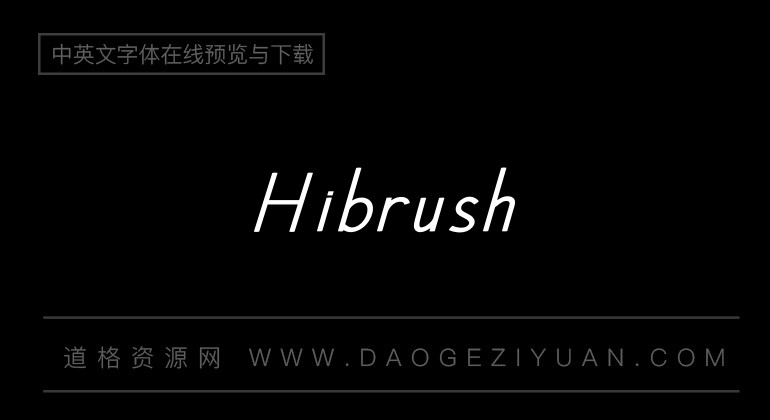
Hibrush 是一款由著名设计师 David Berlow 所设计的字体,它是一款非常优秀的斜体字体,具有非常强烈的视觉冲击力和非常独特的设计风格,它的字体结构设计紧凑而精细,可以让文字具有良好的表现力和清晰度。Hibrush 字体也可以用于多种不同的文字排版,比如标题、正文、图片文字等,能够更好地展现文字的艺术性和美感。内容介绍
Hibrush是一款非常不错的手写艺术字体,具有很好的视觉感,适合于文化类的宣传设计、商业类品牌的广告和产品包装设计以及个性化文字排版等较多场景。